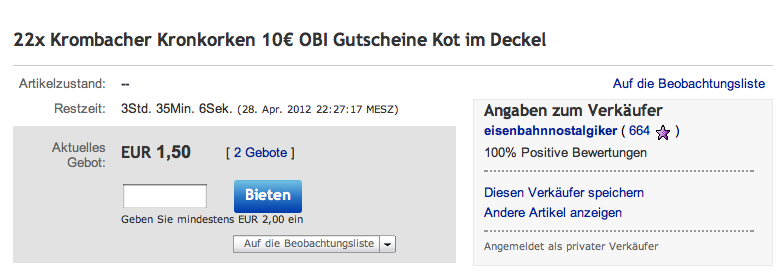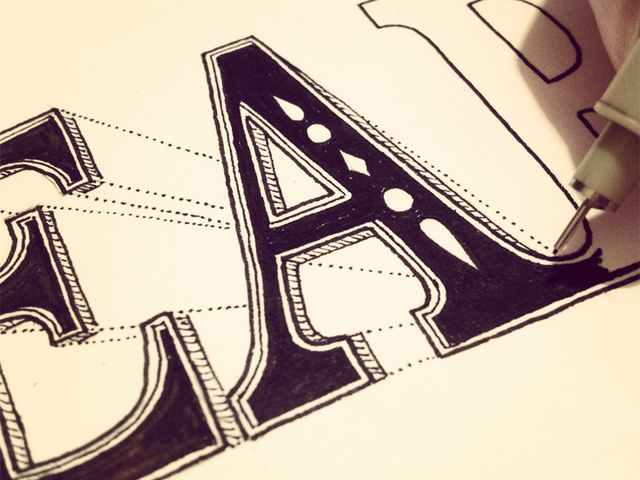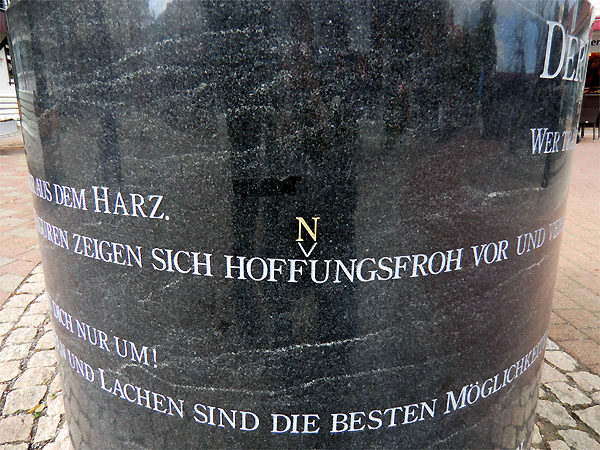
Deine Aussage … hat einfach Erwartungen geweckt, die leider nicht erfüllt werden.
Entschuldige bitte! Das kommt davon, wenn man sich vor voller Begeisterung zu einem Eintrag nebenbei hinreißen lässt, ohne diesen vorher noch einmal auf eventuelle Missverständnis-Quellen abzuklopfen. :-(
Leider ist das Original ja verbrannt. Aber vielleicht willst Du bei Deinem nächsten Ausflug Richtung Norden mal im Kloster Ebstorf oder beim Lüneburger Museum vorbei schauen. Vielleicht wäre das eine »Entschädigung«:
1950 machte sich der Grafiker Rudolf Wieneke (Bispingen/Württ.) an die Arbeit, hiervon im Gerbdruckverfahren vier originalgroße Karten auf Ziegenleder-pergament zu drucken und einzeln von Hand zu kolorieren. Eine dieser Kopien befindet sich heute im Kloster Ebstorf, die zweite im Lüneburger Museum. Mehr
Die können sich dafür die dekorative Bodoni von Jonny Holmes ansehen. : )
Oh, schön, die würde ich mir wohl auch an die Wand nageln ...
Heute gab es im Penny-Markt deutschen Spargel. Auch ein Siegel auf der Verpackung weist auf die Herkunft hin. Nur diese scheint wohl nicht aus deutschen Landen zu stammen. :shock:
Bei ebay …
Gestern am »Jungbrunnen« im schönen Bad Harzburg entdeckt …
Vielleicht ist dort ja Norden und man wollte das eigens betonen.
ja … grad das gespiegelt sein (oder muss man „das Gespiegelt-sein“ schreiben?) finde ich total komisch. Kann sich jemand einen Grund dafür denken?
Das soll aussehen wie Nessie (Loch Ness), weil der Erfolg von Steuerberatung genauso ein Mythos ist. :!: